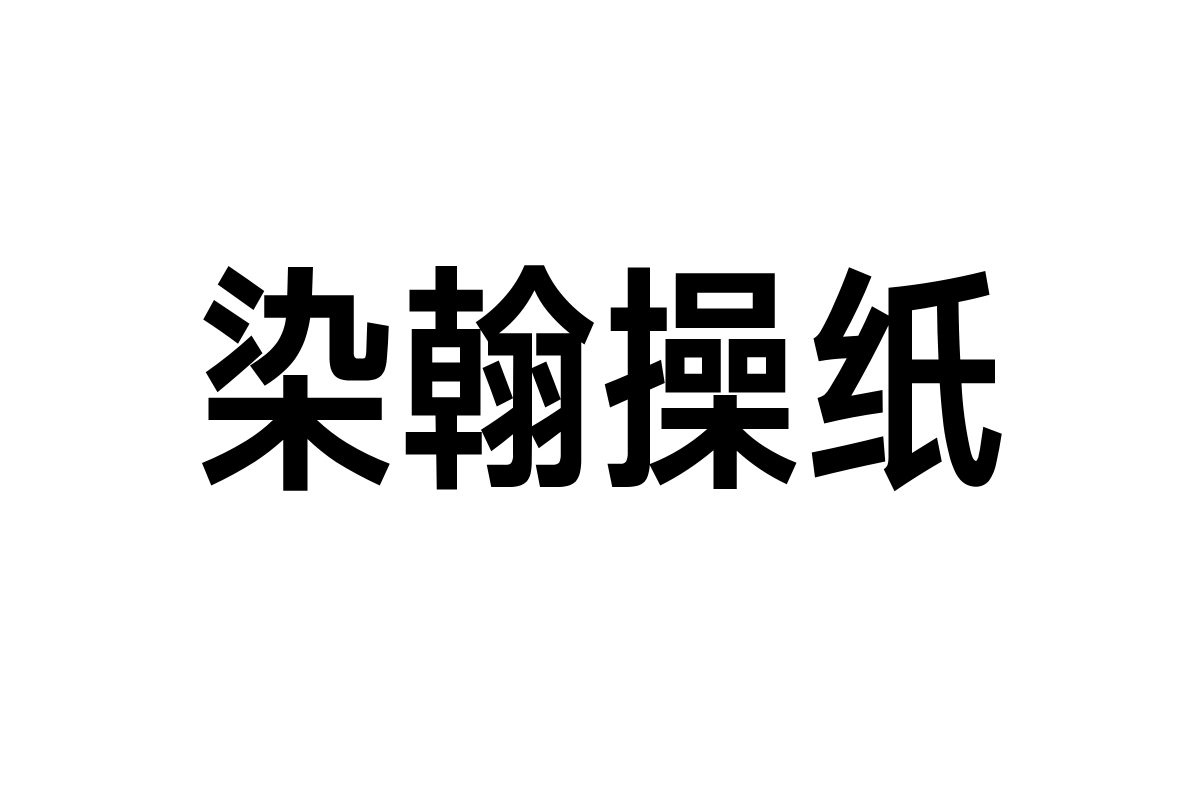
汉仪旗黑X3是一款具有独特风格的字体,它采用了现代的设计元素和简洁的线条,给人一种清晰、有力的感觉。这款字体的特点是笔画粗细适中,结构紧凑,适合用于各种需要强调文字的地方,如标题、广告、标志等。同时,它的可读性也非常好,无论是在哪种设备上使用,都能保证良好的视觉效果。总的来说,汉仪旗黑X3是一款非常实用的字体,值得大家尝试使用。